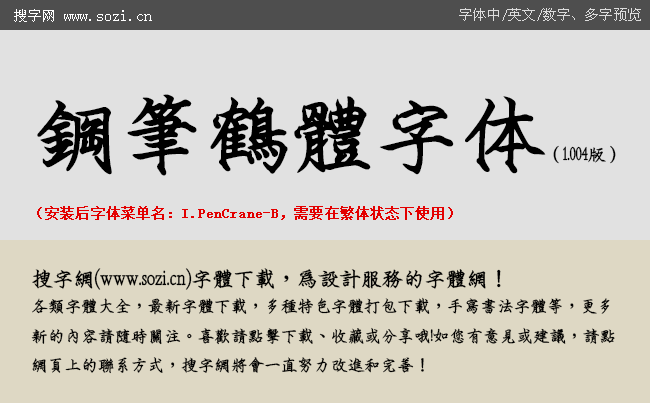
鋼筆鶴體字體
搜字網(wǎng)提供一款鋼筆鶴體字體中文鋼筆書法字體下載,鋼筆鶴體字體是一款繁體中文硬筆書法字體,字體端正,字形大方,整體效果十分出色,適合應(yīng)用于廣告設(shè)計(jì)、名片設(shè)計(jì)、包裝印刷、兒童產(chǎn)品設(shè)計(jì)等應(yīng)用。